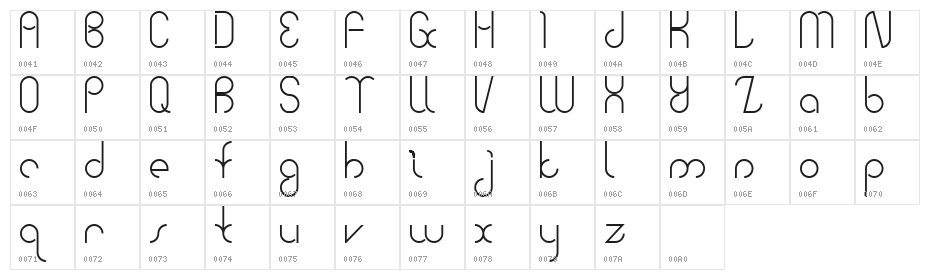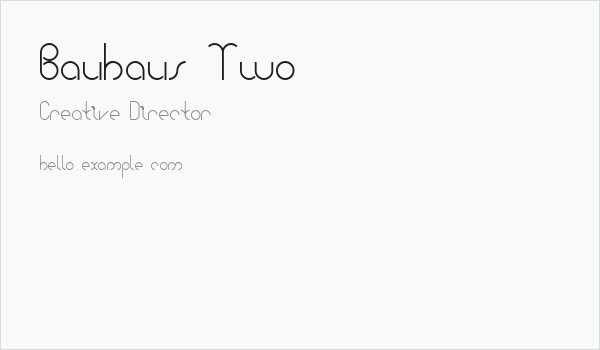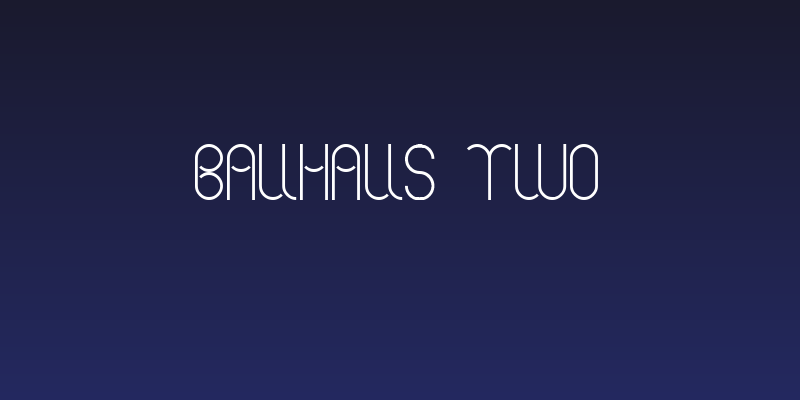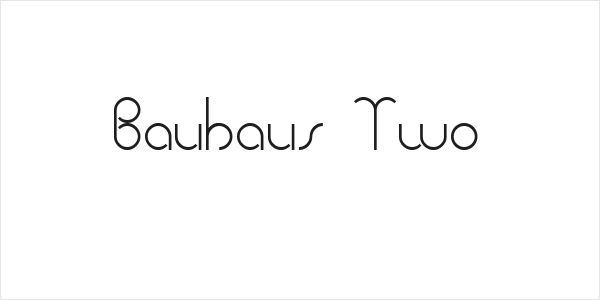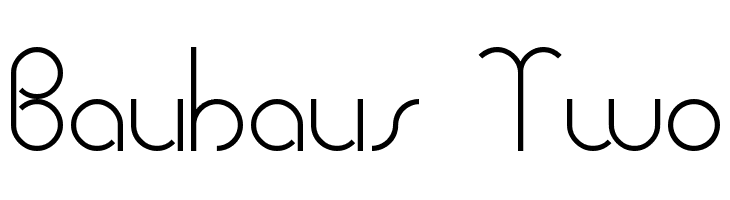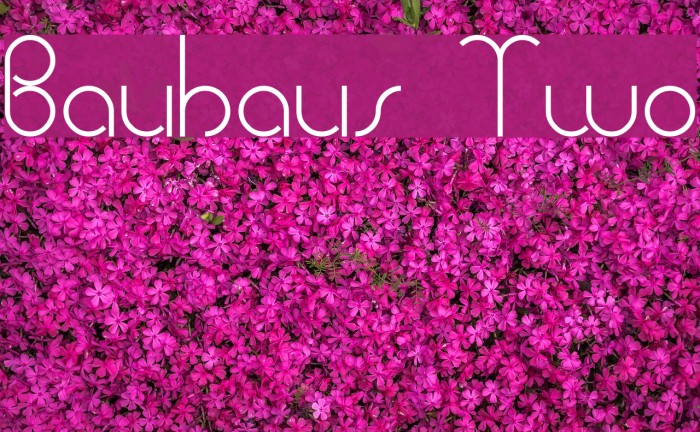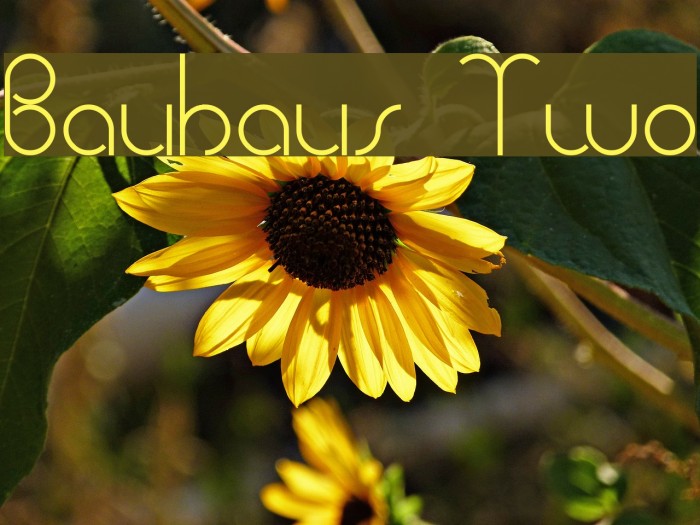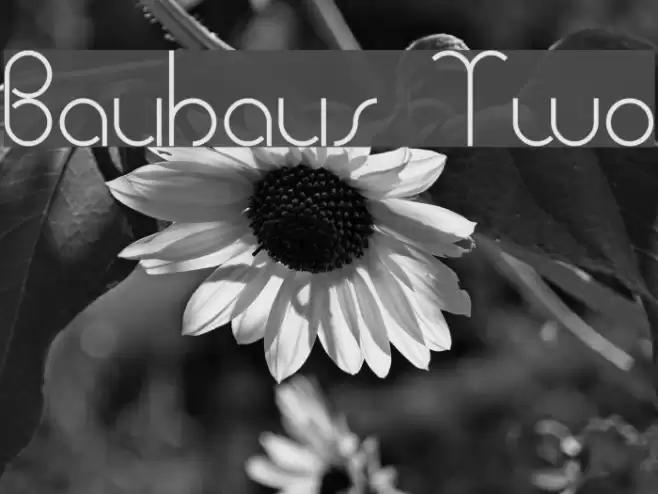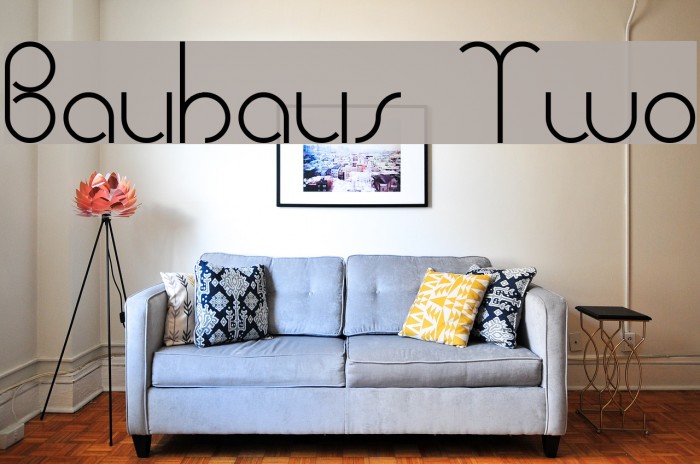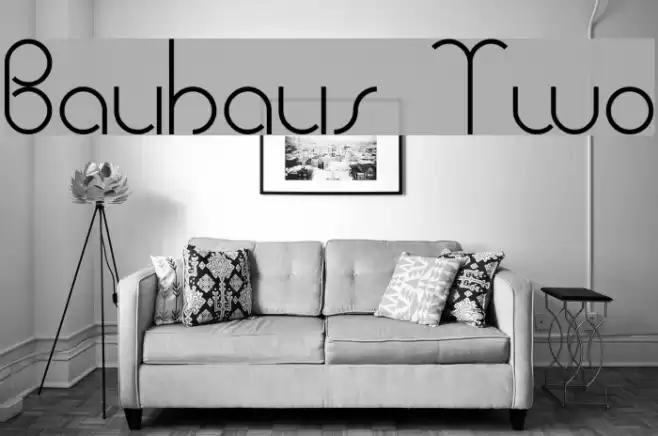
Bauhaus Two Font
| Nom | Bauhaus Two |
| Projets proposés | Ideal for modern branding, posters, and digital media where a clean, contemporary look is desired. |